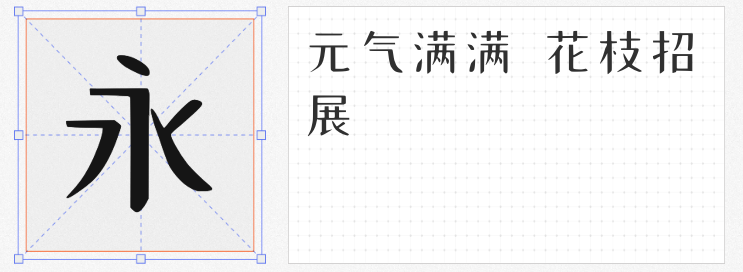
在国潮复兴的浪潮中,设计如何以低成本实现高质感的文化表达?这四款免费商用字体以AI技术与传统书法的融合创新,为设计师提供了兼具艺术性与实用性的解决方案。无论是海报、包装还是品牌视觉,它们都能以独特的东方韵味赋能创意落地。
基于颜真卿《多宝塔碑》算法生成,这款字体完美复刻了颜体“丰腴厚重”的笔触精髓。AI精准捕捉书法中的落笔、转笔、藏锋等细节,将传统书法的“收放起伏”转化为标准化字库。其笔画饱满圆融,骨架刚劲挺拔,尤其适合需要传递历史厚重感的场景。例如,在非遗文化宣传海报中,以深棕色为底,搭配烫金工艺的东方大楷标题,可瞬间营造出“古朴庄重”的视觉氛围,同时AI生成的规范结构确保了远距离阅读的清晰度。
以《爨宝子碑》为灵感,刀隶体通过AI强化了三角点折弯与横画“雁尾”的锋芒,在隶书的方笔意趣中注入现代张力。其结构打破常规均衡,布白大胆出奇,看似“险象环生”,实则暗合书法艺理。这种“稚拙倔强”的气质,使其成为文创产品包装的绝佳选择。例如,在国潮文具套装设计中,以灰白色水墨为背景,搭配暗红色刀隶体标题,可形成“传统与叛逆”的强烈对比,精准狙击年轻消费者的审美痛点。
由字体家AI神笔与书法家叶根友联合打造,字体家AI造字霸行体将行书的流畅与AI的精准完美结合。其笔画粗细对比强烈,转折处硬朗利落,既保留了手写书法的温度,又通过AI优化提升了排版适配性。在影视海报设计中,霸行体可胜任标题与副标题的双重角色:以渐变金属色呈现,能强化“武侠江湖”的豪迈感;若搭配水墨飞白效果,则可传递“诗意山水”的悠远意境。
以“站酷小薇LOGO体”为范本,这款字体通过AI大模型重构出干净利落的现代风格。其笔画去除了多余装饰,仅保留最核心的骨架结构,在极简中暗藏东方哲学。在茶饮品牌视觉系统中,礼品卉自由落体体可与留白设计形成呼应:以浅绿色为底,搭配细长的字体比例,既能传递“清新自然”的品牌调性,又能通过AI生成的微妙弧度避免过于生硬,实现“少即是多”的设计境界。
这四款字体证明:国风设计无需昂贵授权,也能通过科技与传统的碰撞焕发新生。它们不仅降低了创意门槛,更以开放共享的姿态,推动东方美学走向更广阔的舞台。